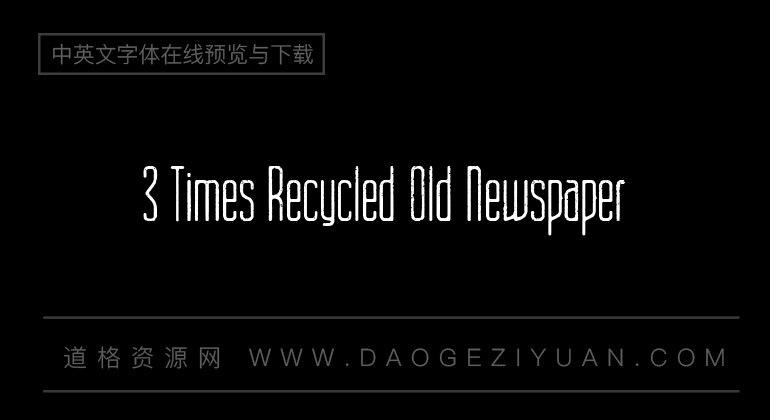
3 Times Recycled Old Newspaper
吗? 3 Times Recycled Old Newspaper 字体是一款具有古老新闻报纸风格的字体。它的特点是字体的线条粗细不一,有点像手写的样子,拥有较强的时代感,有助于增强文本的可读性。它能够更好地展现出新闻报纸的气息,也可以用于复古风格的设计中。
3 Times Recycled Old Newspaper是一款非常不错的手写艺术字体,具有很好的视觉感,适合于文化类的宣传设计、商业类品牌的广告和产品包装设计以及个性化文字排版等较多场景。